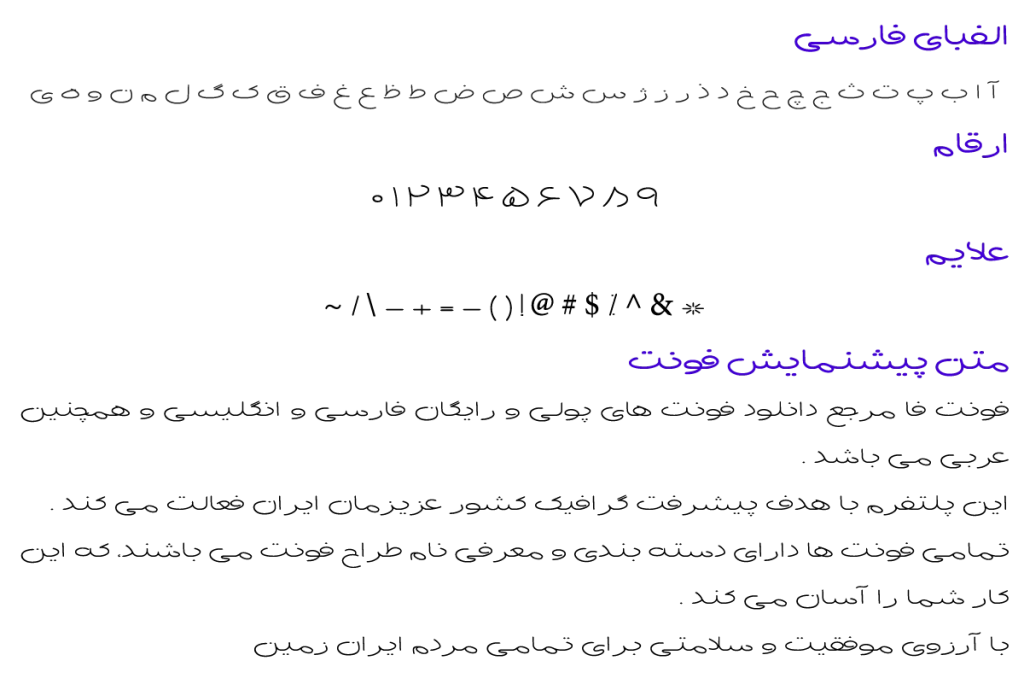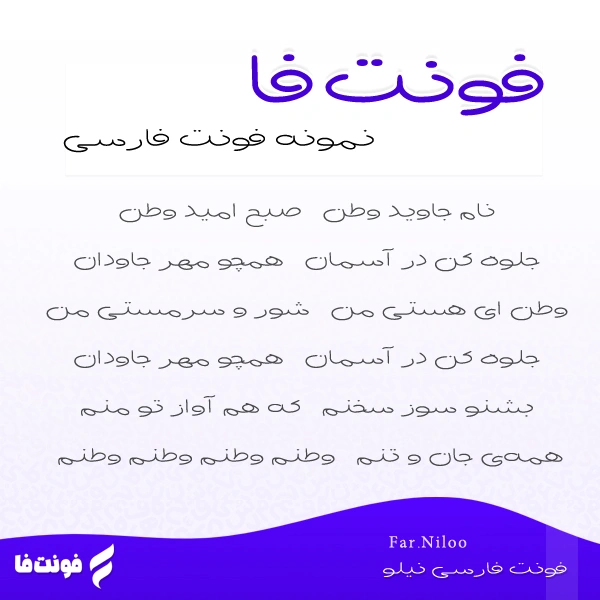
فونت فارسی نیلو – Far Niloo
طراح فونت: ابوالفضل سيل سپور نوع فونت: فونت دست نویس
توضیحات و معرفی فونت نیلو
فونت فارسی نیلو ( Far Niloo ) از مجموعه فونت های سری Far می باشد، همینطور نوع فونت دست نویس می باشد.
فونت زیبای مرتبط توسط ابوالفضل سيل سپور در سال 1390 طراحی و ساخته شده است.
همینطور فونت Far Niloo در 2 وزن پر رنگ و معمولی است.
در تصویر زیر، پیش نمایشی از این تایپ فیس را همراه با شعر زیبای فارسی میبینید.